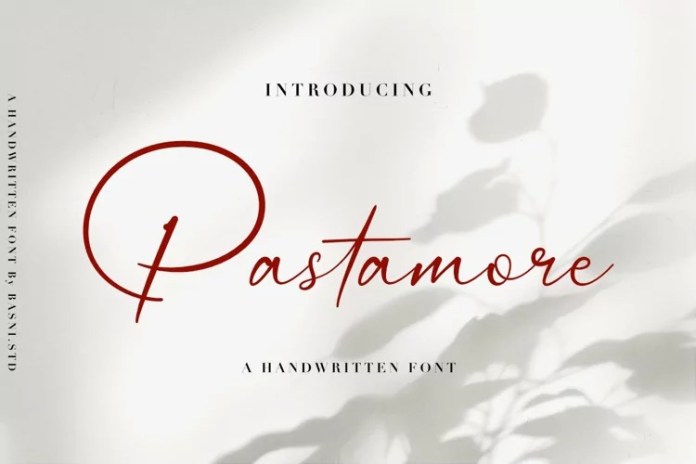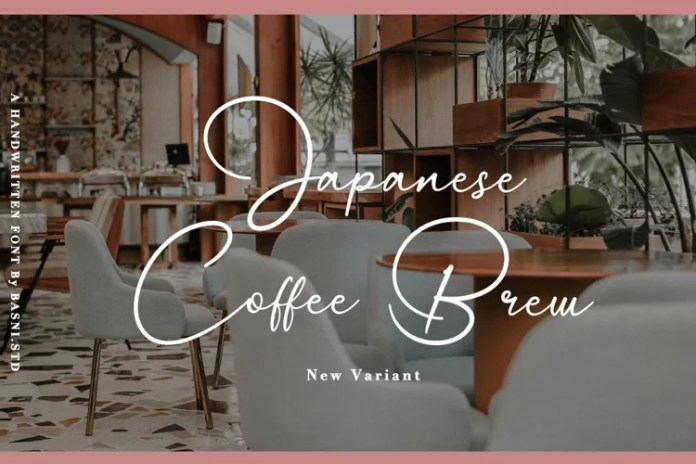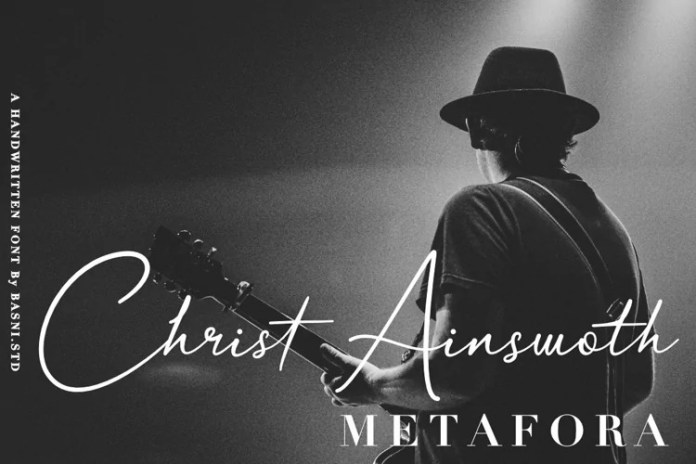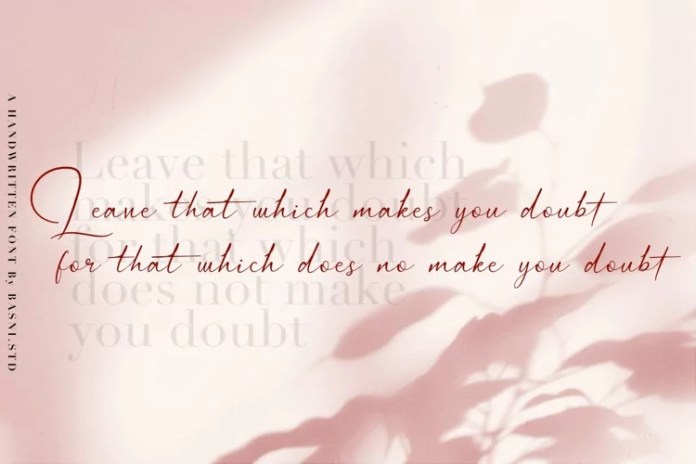
Pastamore 字体下载
Pastamore 字体下载,这款字体结构工整、笔画清晰,兼顾美观与易读性,适用于标题、正文、海报、包装、LOGO 等多种场景。字形优雅稳定,风格百搭耐看,适配日常排版与创意设计,让文字呈现更舒适、更具质感。Pastamore 字体下载一笔一画,皆是细节,以均衡的比例、流畅的线条打造舒适视觉体验,字形端正大气,风格简约现代。无论是商业设计、品牌宣传还是日常排版,都能轻松驾驭,让文字更有格调与力量。Pastamore 字体下载字体下载。
Pastamore Script 字体介绍
It’s a handwritten signature style font crafted & designed by Basnistd, with a soft style and has an elegant nuance, classy and natural. Pastamore is perfect for sign, branding, websites, red wine labels, and editorial designs. Includes all upper and lower case letters, multilingual support, punctuation, binding and initial and final swash. everything can be easily accessed using software that supports OpenType.